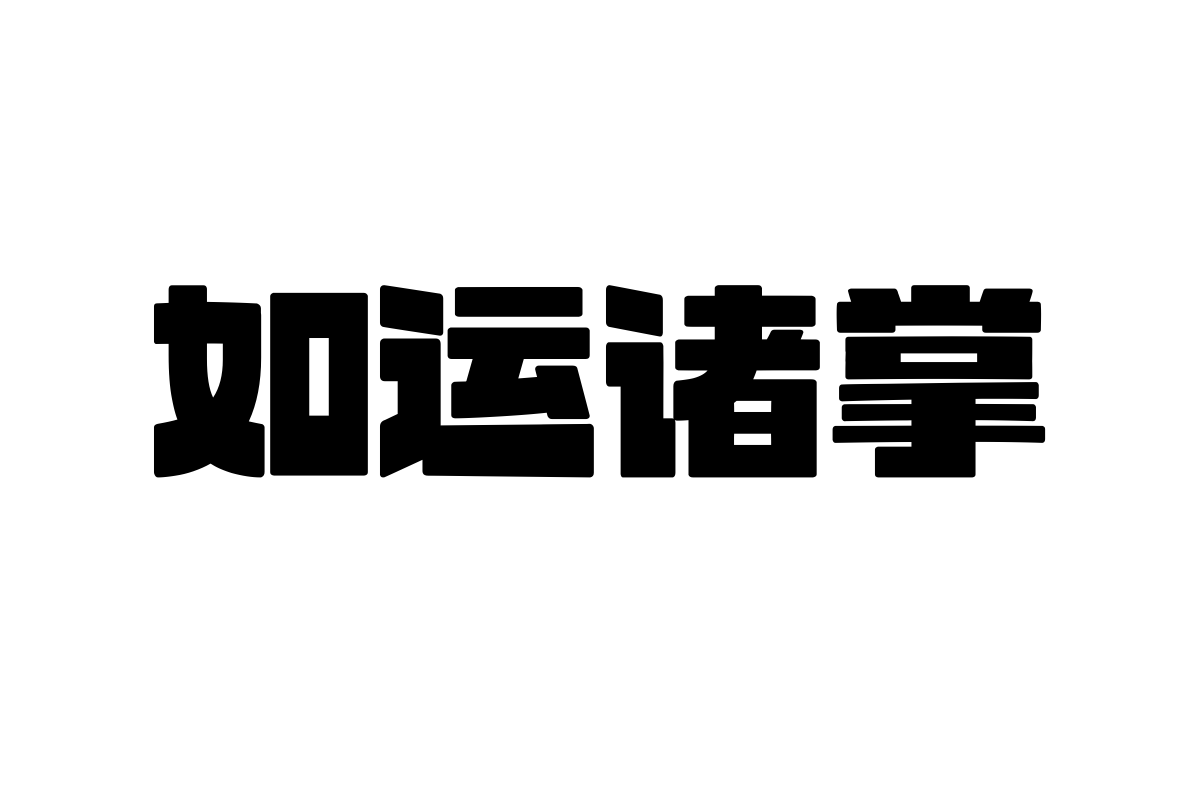
上首魔方体是一款具有独特设计感的中文字体,它采用了魔方体的设计理念,将字母和数字巧妙地融合在一起,形成了一种独特的视觉效果。这种字体的特点是:
1. 字形美观:上首魔方体在字形设计上非常讲究,每一个笔画都经过精心雕琢,使得整个字体看起来既优雅又富有艺术感。
2. 风格独特:上首魔方体不同于传统的宋体、黑体等字体,它有着自己独特的风格,给人一种新颖、别致的感觉。
3. 适用性强:上首魔方体不仅适用于印刷品,也适用于电子屏幕显示,无论是在报纸、杂志、书籍还是网页上,都能展现出其独特的魅力。
4. 易于识别:由于上首魔方体的字形独特,因此非常容易被人们所识别,这对于广告设计、标志设计等场合来说是非常有利的。
总的来说,上首魔方体是一款非常有特色、极具创意的中文字体,无论是用于印刷还是电子屏幕显示,都能给人带来不一样的视觉体验。